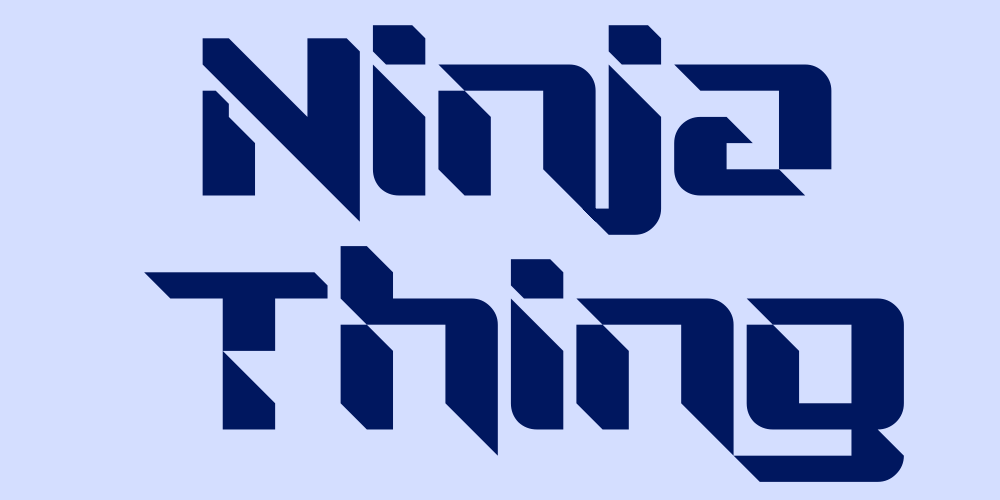
Ninja Thing font – Fonte Grátis
Ninja Thing font
Aqui está uma descrição para a página de download da font ‘Ninja Thing’ na categoria de fonts Display: Com linhas elegantes e formas arredondadas, Ninja Thing é uma font cuidadosamente projetada que se destaca ao misturar elementos futuristas com um toque animado. Seu design irônico se encaixa perfeitamente em aplicações gráficas como logotipos de empresas, editoriais criativas ou elementos digitais para sites e aplicativos. Ninja Thing é uma escolha ideal para os criadores que desejam dar um toque único a seus projetos, seja ele através de texturas ondulantes, formas dinâmicas ou personalizações sutis. Suas linhas fluidas permitem criar visuais interessantes e vibrantes sem comprometer o legibilidade. Ideal para uma gama de ambientes gráficos onde você deseja adicionar um toque irônico e visualmente atraente, Ninja Thing é uma font que não se limita ao uso tradicional. Seu design moderno e seu caráter único o tornam um recurso valioso tanto para designers profissionais quanto para criadores de conteúdos pessoais.